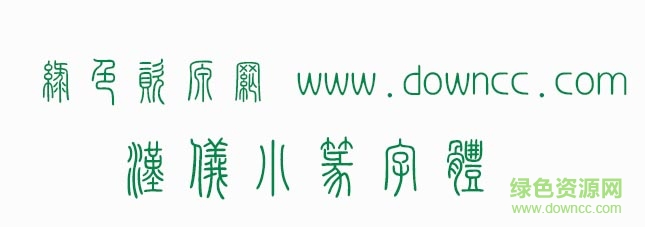
漢儀小篆體字體相對(duì)與篆體粗細(xì)不勻的線條變得均勻柔和了,隨實(shí)物畫出的線條十分簡(jiǎn)練生動(dòng),是在篆體中比較常見的,我們將該字體下載提供給您,歡迎您到綠色資源網(wǎng)下載使用。
漢儀小篆體是秦朝時(shí)代通行的漢字字體,和現(xiàn)在漢字區(qū)別不大,可是普通人識(shí)別依然有不小的難度。他有著美觀典雅的韻味,在字里行間散發(fā)著青春的活力氣息。